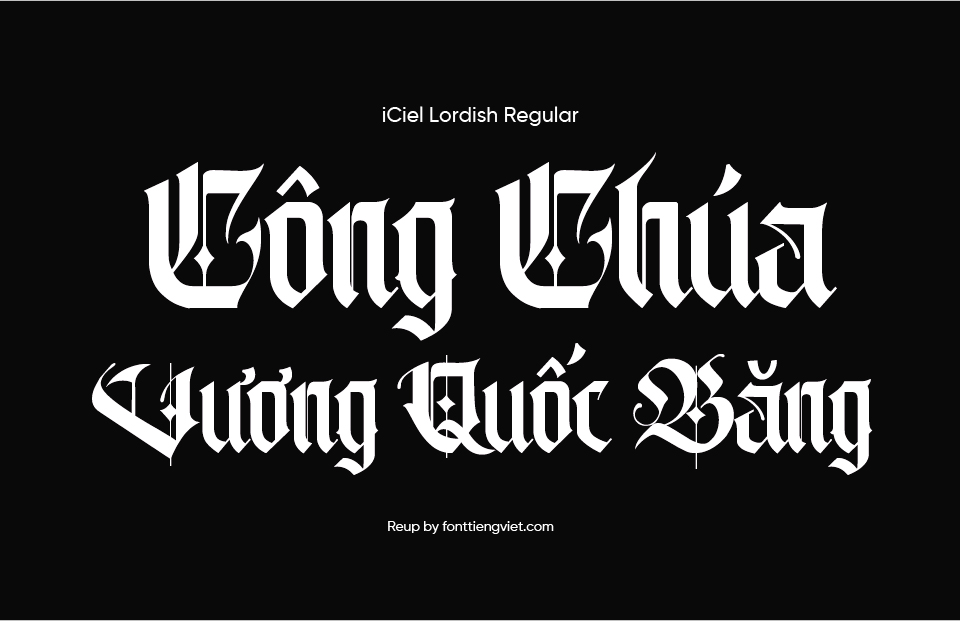
Giới thiệu về Font Việt hóa iCiel Lordish
Trong thế giới thiết kế đồ họa, việc lựa chọn một bộ Font Chữ phù hợp đóng vai trò quyết định đến linh hồn của tác phẩm. Font Việt hóa iCiel Lordish là một trong những bộ font mang phong cách Gothic kết hợp hiện đại đầy ấn tượng. Với các đường nét sắc sảo, mạnh mẽ nhưng không kém phần uyển chuyển, bộ font này giúp các bạn học sinh và nhà thiết kế tạo nên những sản phẩm mang tính nghệ thuật cao. Đặc biệt, phiên bản iCiel Lordish đã được tối ưu hóa tiếng Việt, giúp người dùng sử dụng thuận tiện mà không lo lỗi hiển thị hay thiếu dấu.
Đặc điểm nổi bật của iCiel Lordish
Bộ font này nổi tiếng với các ký tự được trau chuốt tỉ mỉ, lấy cảm hứng từ những bản viết tay cổ điển phương Tây. Mỗi con chữ trong Font Việt hóa iCiel Lordish đều mang một cá tính riêng biệt, phù hợp cho các tiêu đề lớn, bìa sách, hoặc các dự án truyền thông cần sự trang trọng và huyền bí. Nhờ cấu trúc rõ ràng, font chữ này không chỉ đẹp mắt mà còn giữ được độ đọc hiểu tốt trên nhiều nền tảng khác nhau.
Ứng dụng Font Việt hóa iCiel Lordish trong thiết kế
Tại môi trường học đường, giáo viên và học sinh có thể sử dụng font này để thiết kế báo tường, thiệp mời hoặc các slide thuyết trình về chủ đề lịch sử và nghệ thuật. Sự độc đáo của iCiel Lordish giúp nội dung trở nên nổi bật, thu hút ánh nhìn ngay từ lần đầu tiên. Ngoài ra, các nhà thiết kế tự do thường dùng nó cho logo, bao bì sản phẩm hoặc áo thun theo phong cách đường phố. Việc cài đặt font cũng rất đơn giản, tương thích tốt với các phần mềm phổ biến như Photoshop, Illustrator hay Canva.
Lưu ý khi sử dụng font Gothic
Dù rất đẹp, nhưng vì đây là dòng Gothic, bạn nên sử dụng Font Việt hóa iCiel Lordish cho các đoạn văn ngắn hoặc tiêu đề thay vì nội dung văn bản dài. Điều này giúp bố cục tổng thể hài hòa và tránh gây mỏi mắt cho người xem.